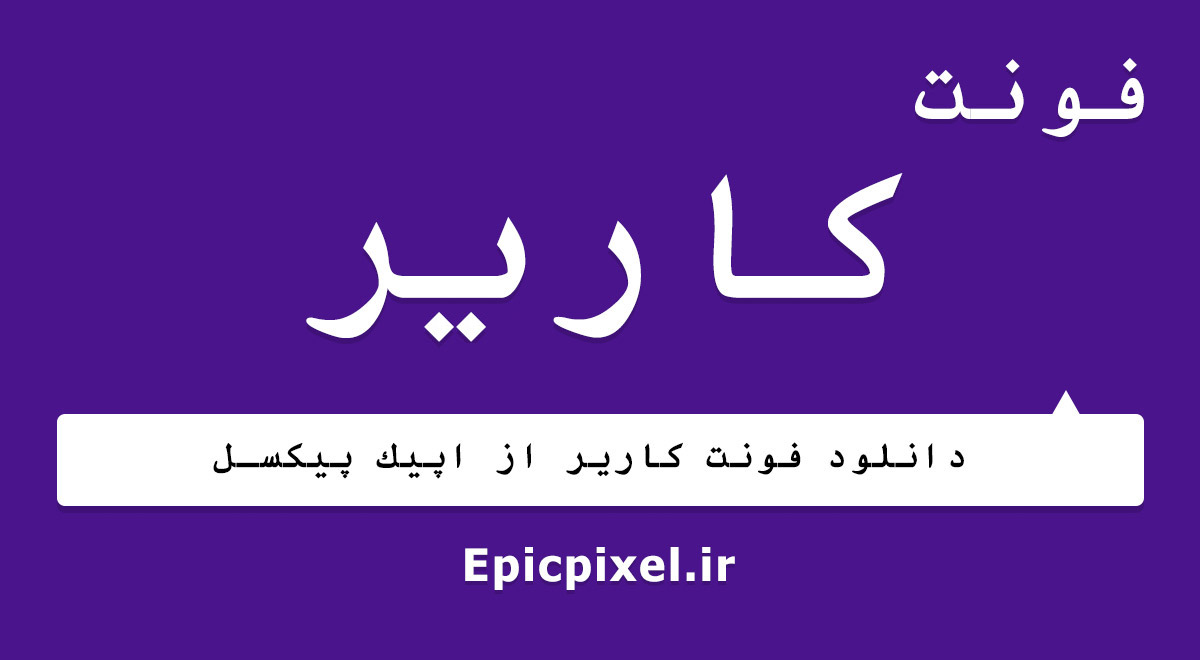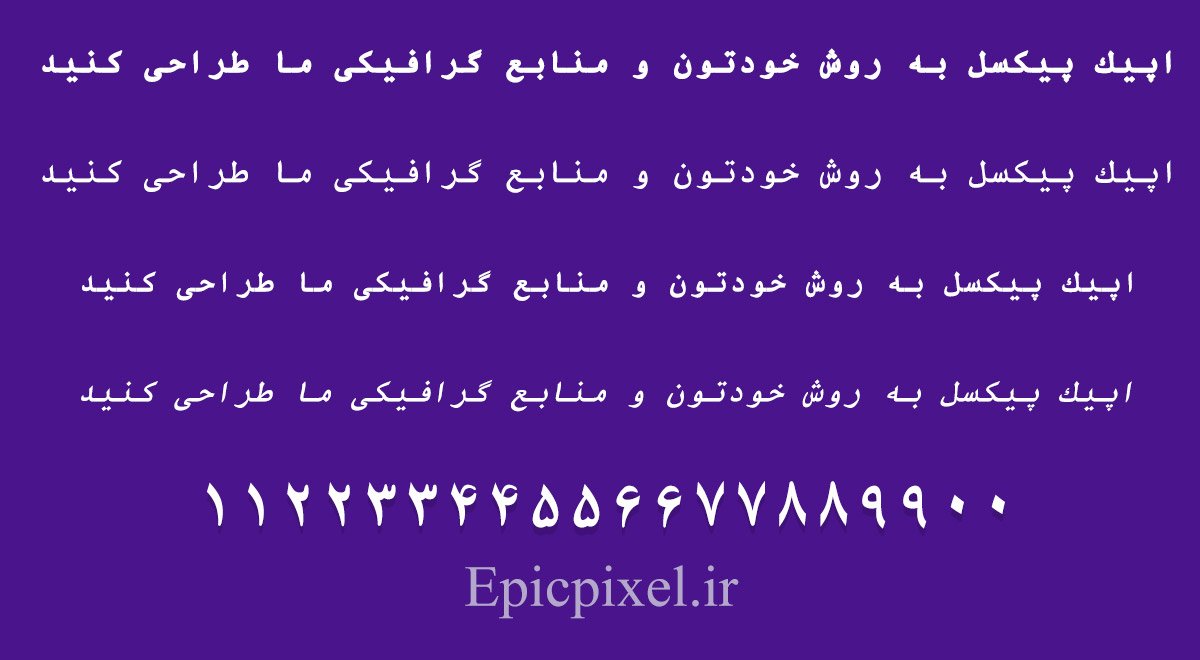
فونت کاریر فارسی (رایگان) گزینه ای بی نظیر برای طراحان و کسب وکارهای دیجیتال است که به دنبال ترکیب کارایی و زیبایی هستند. این فونت با قالب استاندارد Courier طراحی شده که از خوانایی بالا در هر اندازه ای برخوردار است و برای چاپ ، طراحی وب ، و حتی اپلیکیشن های موبایل مناسب است
و به کاربران اجازه می دهد بدون نیاز به تنظیمات پیچیده، از آن در پروژه های مختلف استفاده کنند. همچنین، پشتیبانی از کاراکترهای لاتین باعث می شود برای طراحی های دو زبانه (فارسی و انگلیسی) ایده آل باشد
. این فونت به دلیل سادگی و ظرافت خطوطش ، برای متن های طولانی ، تیترها و حتی لوگوها قابل استفاده است